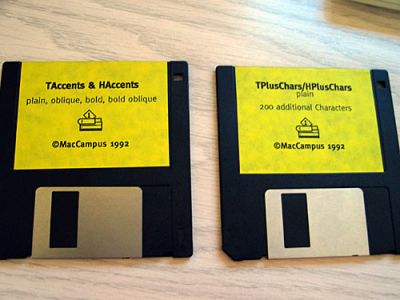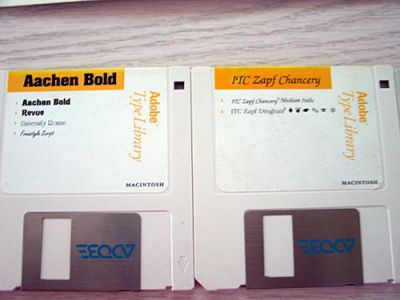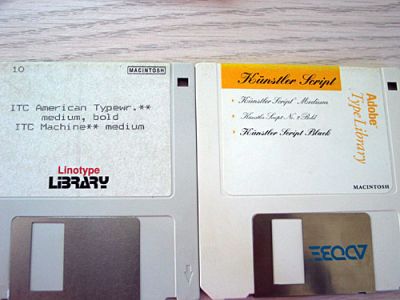
Eure erste gekaufte Schrift?
Was war eure erste gekaufte Schrift und warum musste es genau diese sein?
Bei mir wars Emigres »Template Gothic« ca. 1998/99. Nachdem ich während meiner Ausbildung nur Corel- und Freefonts um mich herum hatte, musste es mal etwas völlig anderes, »trendiges« sein. Ohne konkreten Auftrag. Ich wollte sie einfach haben.
> Nachdem ich während meiner Ausbildung nur Corel- und Freefonts um mich herum hatte ...
ahh, danke ralf. bin ich nicht der einzige ...
hatten wir die gleiche ausbildungsstätte? ;)
bei mir waren es akzente die wir für fremdsprachensatz benötigten,
danach kamen die üblichen verdächtigen. privat waren es die apply
fonts, die ich dann gleich mit in die firma geschleppt habe wo alle
staunten ;)
die einzigen von den alten disketten, die ich vor dem hochwasser
noch retten konnte sind diese:
Meine erste selbstgekaufte Bleisatz-Schriften:
Palatino mager, 12 p
Palatino kursiv, 12 p
Dieser Palatino-Kauf war reine Sentimentalität.
Davon hatte ich einen ganzen Schrank voll an meinem letzten Bleisatz-Arbeitsplatz. Es war meine Leib & Magen-Antiqua. Ich habe sie dann später abgegeben, weil ich als Antiqua-Grundschrift dann doch die Weiß-Antiqua bevorzugte.
Meine erste digitalisierte Schrift:
Kabel Medium
Kabel Demi
Kabel Bold
Mit der Kabel ging es mir wie mit meiner Frau, als ich sie kennenlernte. Das darf sie natürlich nicht wissen, sie würde es nicht verstehen. Rudolf Kochs Koch-Antiqua fand ich schon bemerkenswert. Aber als ich die Kabel zum ersten mal sah, war es passiert. Mein Herz fing an zu bummern und ich wußte "Das ist sie.". Seitdem habe ich nach einem Bleisatz-Schnitt gesucht und nie gefunden. Deshalb der Kauf der digitalisierten ITC Kabel-Schnitte.
Und - wieder einmal Murphy: Gestern habe ich dann doch noch einen Schnitt der Bleisatz-Kabel gefunden:
Bei mir waren’s die Fette Gotisch und die Lincoln-Gotisch, weil ich so um 2001 nur Antiqua-Schriften hatte und die Gebrochenen so total anders waren und spannend in ihrer Vielfalt aussahen. Inzwischen schäme ich mich ein bisschen, weil es viel Schönere gibt (p. M.), wie ich inzwischen finde. Die wurden aber als sehr beliebt beworben und waren leicht erwerbbar.
Und jetzt die Frage nach meiner ersten Schrift!? Ich würde mal vermuten, dass es eine Sammelbestellung aus Gill, Frutiger und sonst noch was war. Die Disketten müssten auch noch irgendwo rum liegen.
Da muss ich übrigens noch auf Adobe schimpfen, denn meine größte Fehlinvestition war wohl die Myriad von Adobe, denn mit CS habe ich die gekaufte Schrift noch mal geschenkt bekommen. Da dürften sich wohl einige verarscht vorgekommen, denn die tollen Schriften der Suite dürften wohl einige zuvor vom Mund abgespart gekauft haben.
Die ersten selbstgekauften Schriften, das war noch zu Atari-Zeiten, und es waren peu à peu alle damals erhältlichen Schriften für das Textprogramm Signum! Das waren Pixelfonts für die damalige Nadeldrucker-Auflösung von 360 mal 360 dpi, später für Laser mit 300 mal 300 dpi (für jede Größe extra gezeichnet).
Richtig ernst wurde es dann erst mit dem Umstieg auf Calamus SL. Ab 2001 ging es damit los:
Ein halbes minimum der Akzidenz Grotesk mager, 8pt. Hat mir Herr Bleicke (der hieß echt so) persönlich aus dem lager am Mehringdamm in Berlin geholt und frisch in packpapier eingepackt. Waren etwa 3,5kg, mehr konnte ich mir nicht leisten. Habe den gießzettel nicht zur hand, weil ich in Lissabon bei der ATypI bin, aber es waren wohl so um die 12 a und entsprechend viele der anderen buchstaben. Damit konnte man 3 oder 4 visitenkarten setzen und musste dann wieder ablegen. Da ich aber sonst nur gebrauchte schriften hatte – Block, Lo-Schrift etc – , waren diese glänzenden nagelneuen buchstaben schon was tolles. Hat 350 DM gekostet damals in 1968; das war ein halbes monatsgehalt, wenn man eins hatte. Mein erster Braun-verstärker kostete im gleichen jahr dann 800 DM.
Das blei ist dann 1977 in London beim brand meiner druckerei geschmolzen.